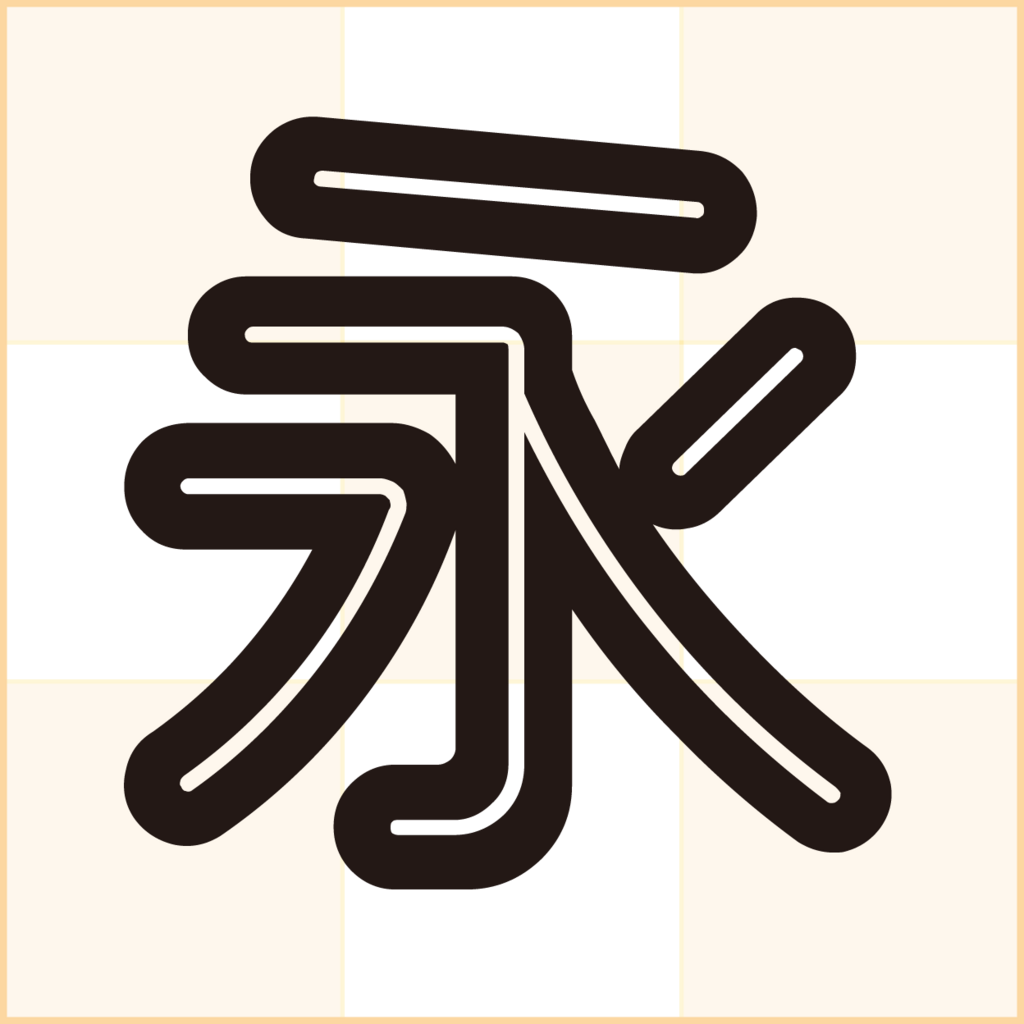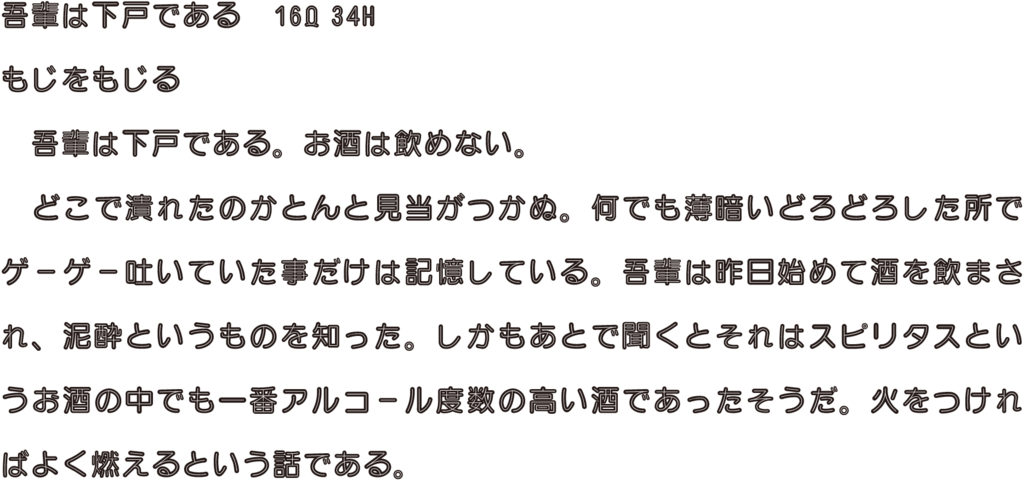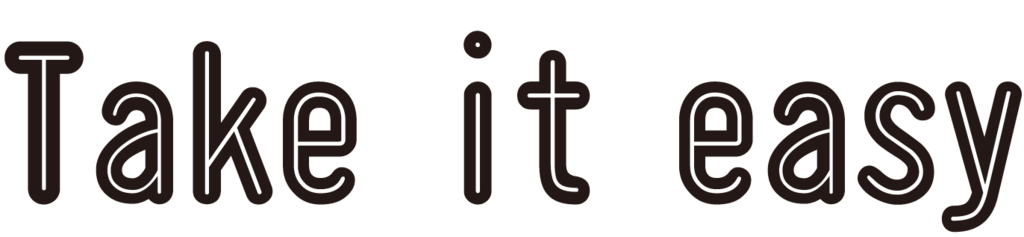
DCインライン
DCインラインは丸ゴシックの角を落とし、よりマイルドなイメージに仕上げた書体。丸ゴシックとしての機能を持ちつつ、中にラインを入れたことで重くなりがちなゴシック体をライトでポップな雰囲気で仕上げており、角張ったイメージが無いため、ビジネス文書よりも手紙などの口語調の文章に適している。また題字部分に使用することで題字がより引き立つ。